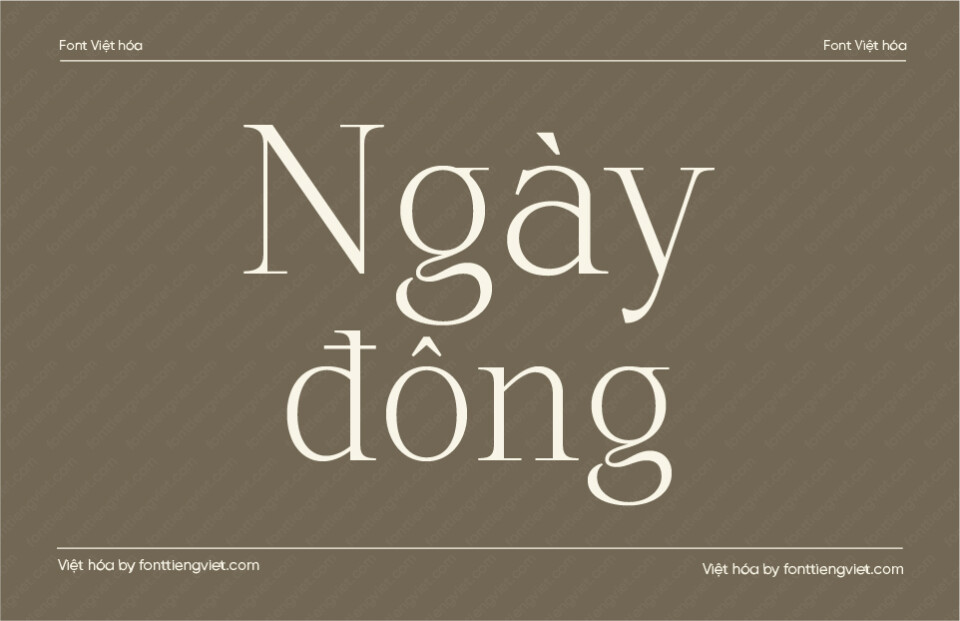
Font Việt hóa 1FTV VIP Askilon – Hiện Đại & Tinh Tế Cho Thiết Kế Mỹ Phẩm
Giới thiệu về Font Việt hóa 1FTV VIP Askilon – Hiện Đại & Tinh Tế Cho Thiết Kế Mỹ Phẩm
Trong thế giới đồ họa hiện đại, việc lựa chọn một bộ Font Miễn Phí chất lượng luôn là ưu tiên hàng đầu của các nhà thiết kế. Font Việt hóa 1FTV VIP Askilon – Hiện Đại & Tinh Tế Cho Thiết Kế Mỹ Phẩm xuất hiện như một làn gió mới, mang đến sự sang trọng và đẳng cấp cho mọi bản vẽ. Đây là bộ phông chữ được tinh chỉnh kỹ lưỡng, hỗ trợ đầy đủ tiếng Việt với các dấu thanh chuẩn xác, giúp người dùng không còn lo lắng về lỗi hiển thị khi soạn thảo nội dung. Với đường nét thanh mảnh nhưng vô cùng dứt khoát, Askilon nhanh chóng chiếm trọn cảm tình của cộng đồng làm đẹp và quảng cáo mỹ phẩm cao cấp.
Đặc điểm nổi bật của Font Việt hóa 1FTV VIP Askilon – Hiện Đại & Tinh Tế Cho Thiết Kế Mỹ Phẩm
Sự kết hợp hoàn hảo giữa nét cổ điển và hơi thở đương đại
Bộ Font Việt hóa 1FTV VIP Askilon – Hiện Đại & Tinh Tế Cho Thiết Kế Mỹ Phẩm không chỉ đơn thuần là một công cụ gõ chữ mà còn là một tác phẩm nghệ thuật. Cấu trúc của các ký tự được thiết kế dựa trên các tỷ lệ vàng, tạo ra sự cân đối tuyệt đối giữa các khoảng trắng và nét mực. Sự hiện đại thể hiện qua các góc cắt sắc sảo, trong khi sự tinh tế lại nằm ở những đường cong mềm mại ở các điểm nối chữ. Điều này tạo nên một tổng thể hài hòa, giúp thông điệp của thương hiệu trở nên chuyên nghiệp và đáng tin cậy hơn trong mắt khách hàng.
Khả năng ứng dụng đa dạng trong ngành công nghiệp làm đẹp
Lý do khiến Font Việt hóa 1FTV VIP Askilon – Hiện Đại & Tinh Tế Cho Thiết Kế Mỹ Phẩm trở thành lựa chọn số một cho ngành mỹ phẩm chính là khí chất mà nó tỏa ra. Khi đặt font chữ này lên các bao bì sản phẩm như serum, kem dưỡng da hay nước hoa, nó ngay lập tức nâng tầm giá trị của sản phẩm đó. Ngoài ra, phông chữ này còn cực kỳ hiệu quả khi dùng cho các tiêu đề tạp chí thời trang, các bài đăng mạng xã hội yêu cầu tính thẩm mỹ cao, hoặc các banner quảng cáo tại các spa và thẩm mỹ viện lớn trên toàn quốc.
Lợi ích khi sử dụng Font Việt hóa 1FTV VIP Askilon cho dự án thiết kế
Tối ưu hóa trải nghiệm người dùng trên các nền tảng số
Không chỉ đẹp trên bản in, Font Việt hóa 1FTV VIP Askilon – Hiện Đại & Tinh Tế Cho Thiết Kế Mỹ Phẩm còn có độ hiển thị cực tốt trên các thiết bị di động và máy tính. Các nét chữ rõ ràng giúp người đọc dễ dàng tiếp nhận thông tin mà không gây mỏi mắt. Điều này cực kỳ quan trọng trong các chiến dịch marketing online, nơi mà sự chú ý của khách hàng chỉ kéo dài trong vài giây ngắn ngủi. Một phông chữ đẹp và dễ đọc sẽ giữ chân người dùng lâu hơn trên trang web hoặc fanpage của bạn.
Sáng tạo không giới hạn với bộ ký tự Việt hóa chuẩn
Việc sử dụng Font Việt hóa 1FTV VIP Askilon – Hiện Đại & Tinh Tế Cho Thiết Kế Mỹ Phẩm giúp các bạn học sinh, sinh viên và các nhà thiết kế trẻ tại Việt Nam tự tin hơn trong việc truyền tải ý tưởng. Bạn sẽ không gặp phải tình trạng nhảy font hay mất dấu khi gõ các từ tiếng Việt phức tạp. Điều này giúp quy trình làm việc trở nên trôi chảy, tiết kiệm thời gian chỉnh sửa hậu kỳ và đảm bảo tính thống nhất cho toàn bộ bộ nhận diện thương hiệu từ logo đến catalogue.
Kết luận về bộ Font Việt hóa 1FTV VIP Askilon